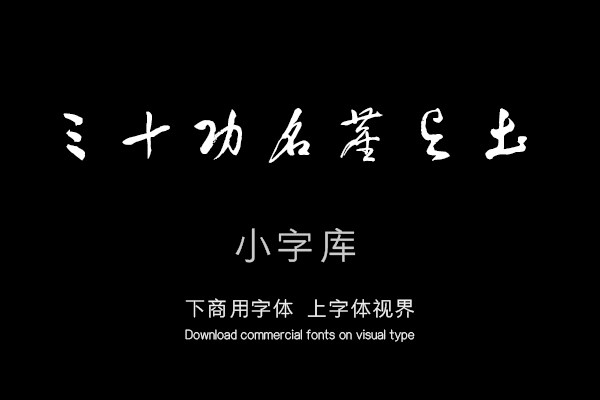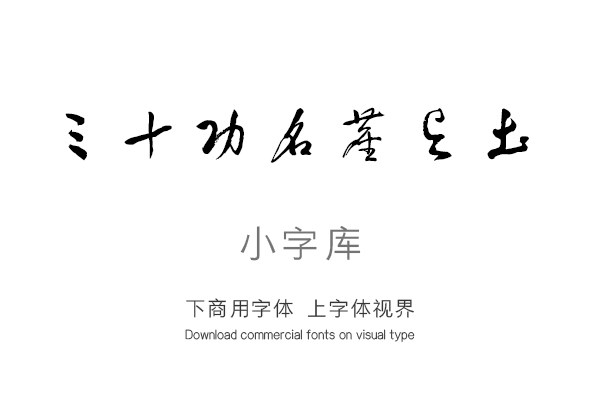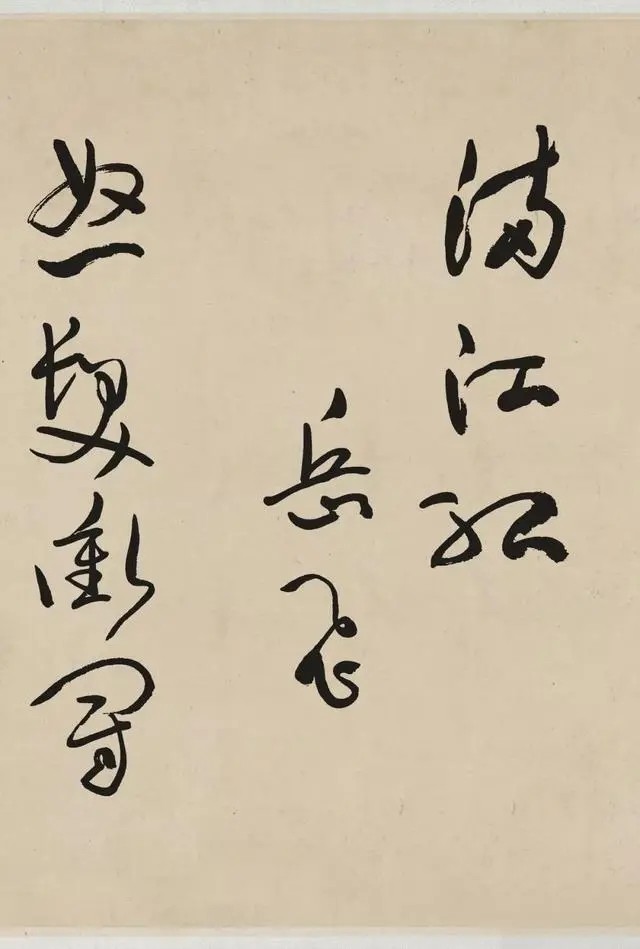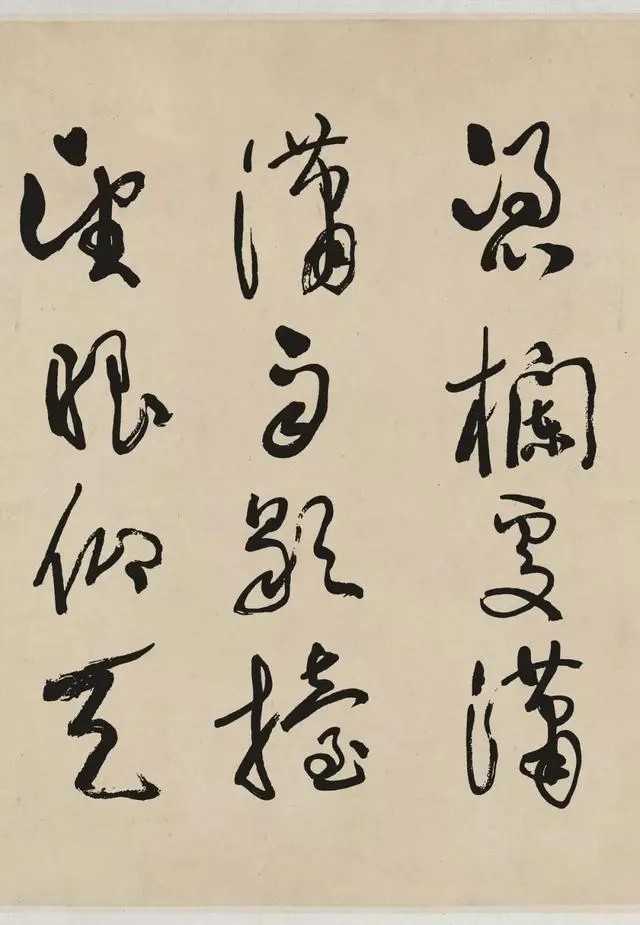
《汉标于右任满江红》是一款根据于右任满江红,经过再次调整制作的小字库,该小字库共收录了该真迹作品中约136个字体。单字授权
《满江红》岳飞;怒发冲冠,凭栏处,潇潇雨歇。抬望眼,仰天长啸,壮怀激烈。三十功名尘与土,八千里路云和月。莫等闲,白了少年头,空悲切!靖康耻,犹未雪;臣子恨,何时灭?驾长车,踏破贺兰山缺!壮志饥餐胡虏肉,笑谈渴饮仇雠血。待从头,收拾旧山河,朝天阙!(李代总统德公正之于右任)